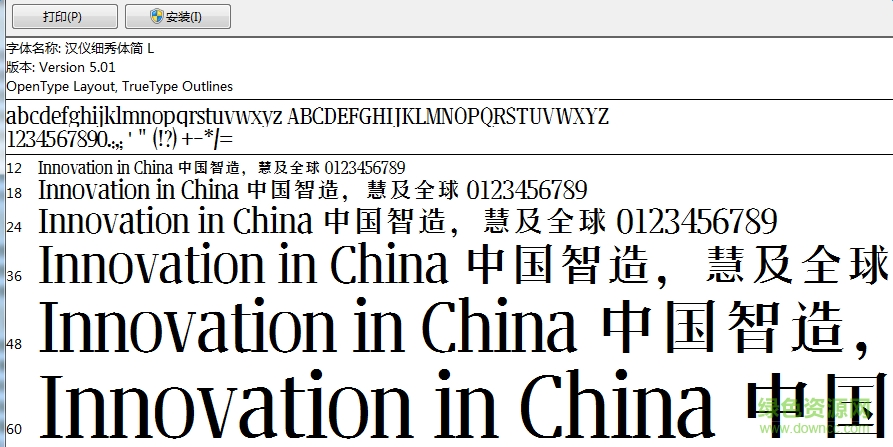
軟件介紹 軟件標簽: 漢儀字體 字體 漢儀細秀體簡是一款漢儀字體庫中的個性字體,可以廣泛應(yīng)用于廣告設(shè)計、宣傳海報、ppt、影視制作以及任何使用文字的領(lǐng)域,有需要的朋友可以免費下載收藏。字體安裝方法方法一:控制面板/字體/文件/安裝新字體;方法二:直接將字體復(fù)制到C:\WINDOWS\Fonts。方法三:針對win7系統(tǒng),用戶只需選中字體右鍵安裝即可。注意事項本站所有字體資源僅供個人學(xué)習與參考,如需商業(yè)使用請到相關(guān)官網(wǎng)授權(quán)。 本字體如果商用,請聯(lián)系漢儀字體官方獲得授權(quán)。 軟件截圖 上一張下一張(1 / 1) 安裝詳細截圖 猜你喜歡 漢儀字體 漢儀字體 漢儀字體有哪些?漢儀字體下載大全收錄了所有好看的、經(jīng)典的漢儀字體合集,漢儀字體是由北京漢儀科印信息技術(shù)有限公司創(chuàng)作,這些字體種類齊全,各具特色、應(yīng)用領(lǐng)域廣泛,喜歡漢儀字體的朋友歡迎來綠色資源網(wǎng)免費下載使用! 查看更多>> 阿里巴巴普惠字體 26.00M/中文/0.8/官方ttf版下載 漢儀天宇風行體 21.41M/中文/5.0/下載 漢儀蘇澤立行楷精修版簡 3.01M/中文/4.0/免費版下載 漢儀正圓(共7款) 17.96M/中文/2.8/ttf免費版下載 漢儀可愛字體打包 41.20M/中文/5.0/14款下載 漢儀曉波花月圓字體 1.89M/中文/0.0/下載 其他版本下載 標題 大小 更新日期 下載 下載地址 電腦版 漢儀細秀簡體 點擊報錯 軟件無法下載或下載后無法使用,請點擊報錯,謝謝! 關(guān)閉報錯反饋 請描述您所遇到的錯誤,我們將盡快予以修正,謝謝! *必填項,請輸入內(nèi)容 本類最新 漢儀孟瑞體ttf v1.0 官方版 漢儀字庫免費 132款 阿里巴巴普惠字體 官方ttf版 漢儀字體打包大全 for Mac 蘋果電腦版_ 共131款字體 漢儀純愛情書拼音體 ttf版 漢儀北魏寫經(jīng)w字體 免費版 相關(guān)文章 Photoshop字體安裝使用方法和技巧 如何解決“無法新增字體”問題 Win 7系統(tǒng)安裝字體方法 網(wǎng)頁字體大小設(shè)置方法 怎么改網(wǎng)頁字體大小 在Linux系統(tǒng)中安裝字體的幾種方法 windows7字體顯示問題:打開某些程序的時候顯示的是亂碼 用戶評論 熱門評論 最新評論 發(fā)表評論 查看所有評論(0) 昵稱: 請不要評論無意義或臟話,我們所有評論會有人工審核. 字數(shù): 0/500 (您的評論需要經(jīng)過審核才能顯示)